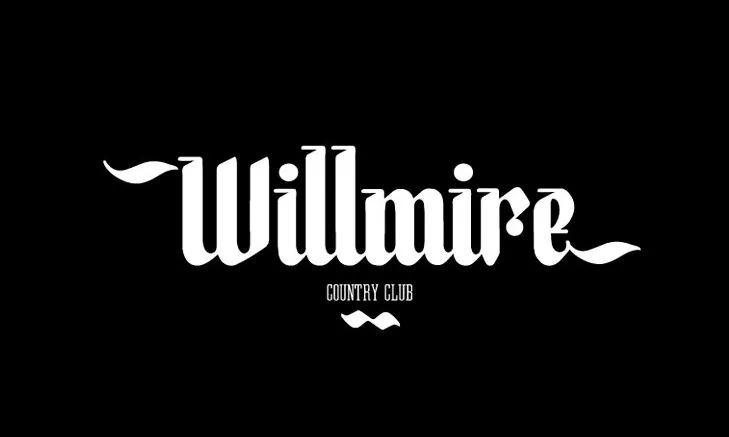
Mortyr Black Font – Download Grátis
A fonte Mortyr Black Font é uma escolha perfeita para quem busca algo diferenciado e único no mundo das fuentes. Inspirada nos estilos antigos e masculinos, ela traz um toque moderno e elegante às suas criações. Ideal tanto para rótulos quanto para outros materiais impressos, Mortyr Black é uma opção ideal para quem quer destacar seu trabalho de forma autêntica e sofisticada. Seja você um designer ou empresário que valoriza o padrão clássico em conjunto com uma modernidade atemporal, a fonte Mortyr Black se destaca como uma escolha cuidadosa. Sua natureza robusta e sua estrutura sóbria garantem que seu design seja resistente e duradouro ao longo do tempo. Seja esse o mote da sua marca ou de seus produtos, Mortyr Black oferece um estilo único para qualquer aplicação visual.